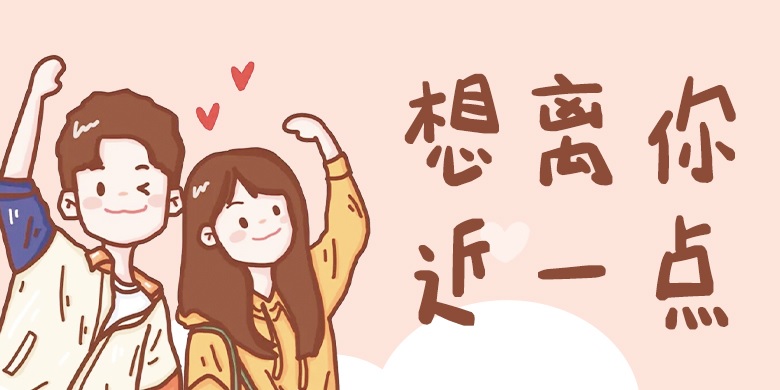
品牌:方正手迹设计师:余丹发行时间:2018字库编码:大陆简体(GB2312-80)分类:创意书写字体属性:精品字
超大的粗细变化,俏皮可爱的构字,打破常规的结构,组成了极具少女气息的没故事的女生。特别是一些转折处,采用大直角的处理,配以俏皮的构字,将可爱的一面表现的淋漓尽致。适用于少年儿童类的书刊、品牌广告和产品包装设计,以及社交网络的个性化用字。